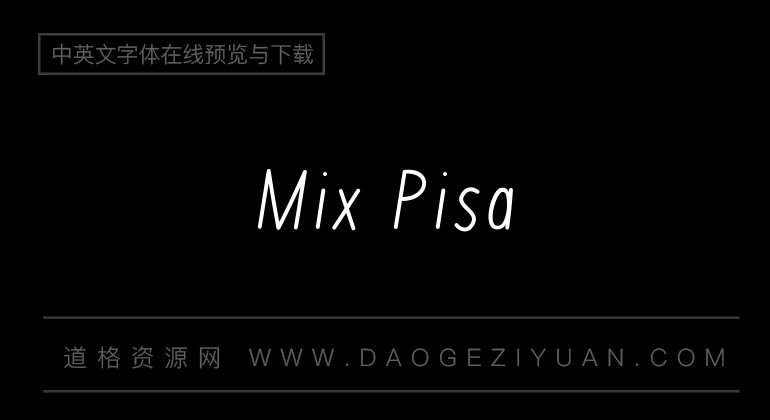
Mix Pisa 是一种非常流行的免费字体,由 Italian Type Designer Francesco Canovaro 创建。它是一种现代风格的字体,设计简洁、优美、通用,并在印刷和屏幕上都非常适用。Mix Pisa 字体家族包括轻、正常、半粗、粗、黑五种字重,每个字重都包括大写字母、小写字母、数字和标点符号,非常实用。它可以用于各种场合,如海报、标志、印刷品、网站、应用程序等。Mix Pisa 字体的优点是具有良好的可读性和可识别性,因此在设计时很容易吸引人们的注意力。内容介绍
Mix Pisa是一款非常不错的手写艺术字体,具有很好的视觉感,适合于文化类的宣传设计、商业类品牌的广告和产品包装设计以及个性化文字排版等较多场景。